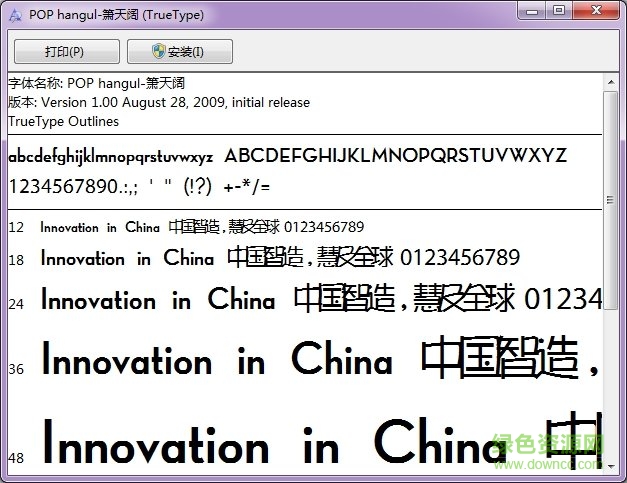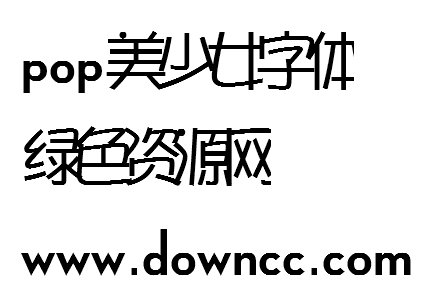
pop美少女字體
美少女字體是一款pop風(fēng)格的藝術(shù)字體,字體有著纖細(xì)圓潤的造型,有著少女般的活潑和熱鬧,更有多種點綴修飾,使其更有獨特魅力,綠色資源網(wǎng)誠意推薦!
pop美少女字體簡介
美少女字體,英文名稱為POPhangul,由簫天闊早期創(chuàng)作,每一個漢字都較為緊貼,卻不顯得擁擠,給人直觀醒目的視覺呈現(xiàn),如果你有藝術(shù)設(shè)計、海報設(shè)計等方面的需要,可以嘗試哦!